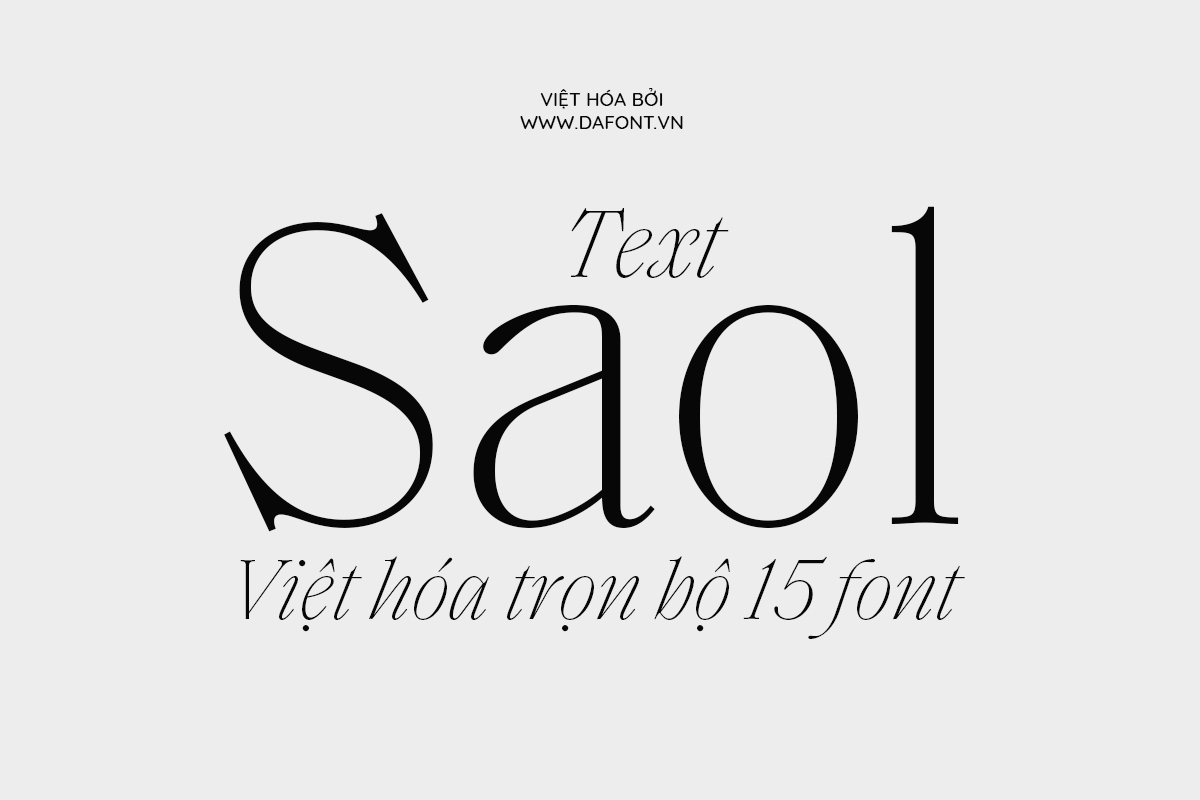
DFVN Saol Text Việt hóa (15 font)
DFVN Saol Text là một phần của bộ font Saol. Đây là phiên bản dành cho văn bản với các nét tương phản giảm để tránh các đường nét mảnh bị mất khi sử dụng ở kích thước nhỏ.
Saol Text bao gồm 7 kiểu đứng và 7 kiểu nghiêng cùng với 1 kiểu Monospaced (là phông chữ có độ rộng cố định, có các chữ cái và ký tự chiếm cùng một lượng không gian theo chiều ngang.)
DFVN Saol Text Việt hóa trọn bộ 15 font
Đặc điểm nổi bật của Saol Text
Phiên bản Text được tối ưu cho các kích thước nhỏ và có độ tương phản vừa phải, giúp tạo ra các hệ thống phân cấp kiểu chữ chi tiết, từ tiêu đề nổi bật đến văn bản dài dễ đọc. Saol Text thường được sử dụng trong các tạp chí và ấn phẩm, mang lại vẻ trang trọng và tinh tế.
DFVN Saol Text Việt hóa - 7 kiểu đứng
Saol Text với 7 kiểu đứng
• Độ tương phản vừa phải: Saol Text có độ tương phản vừa phải, giúp văn bản dễ đọc và không gây mỏi mắt khi đọc lâu.
• Nhiều trọng lượng: Font chữ này có sẵn 7 kiểu khác nhau từ Thin đến Bold, kèm theo phiên bản nghiêng tương ứng.
• Tối ưu hóa cho kích thước nhỏ: Bộ font được thiết kế để sử dụng ở các kích thước nhỏ mà vẫn giữ được độ rõ nét và dễ đọc.
Ứng dụng trong thiết kế
DFVN Saol Text Việt hóa - 7 kiểu nghiêng tương ứng
và 7 kiểu nghiêng tương ứng
• Tạp chí và ấn phẩm: Bộ font này thường được sử dụng trong các tạp chí và ấn phẩm để tạo ra các tiêu đề nổi bật và văn bản dễ đọc. Độ tương phản vừa phải giúp tạo ra sự cân bằng giữa tính thẩm mỹ và tính thực dụng.
• Thiết kế web: Trong thiết kế web, Saol Text có thể được sử dụng để tạo ra các nội dung đẹp mắt. Các trọng lượng khác nhau giúp tạo ra hệ thống phân cấp rõ ràng cho các tiêu đề, đoạn văn bản và chú thích.
• Thương hiệu: Saol Text mang lại vẻ sang trọng và tinh tế, rất phù hợp cho các thiết kế logo, bao bì sản phẩm và các tài liệu quảng cáo.
• Thiết kế đồ họa: Bộ font này có thể được sử dụng trong các thiết kế đồ họa như poster, banner và các tài liệu quảng cáo khác để tạo ra các tiêu đề nổi bật và văn bản dễ đọc.
• Thiết kế sách: Font chữ này cũng rất phù hợp cho việc thiết kế sách, từ bìa sách đến nội dung bên trong. Độ tương phản vừa phải giúp văn bản dễ đọc và không gây mỏi mắt khi đọc lâu.
DFVN Saol Text Việt hóa - Bộ font rất đẹp mắt
Saol Text phù hợp cho nhiều dự án thiết kế.
Dễ dàng kết hợp với nhiều kiểu font
Bạn có thể kết hợp với Saol Display để tạo ra một hệ thống phân cấp typographic hoàn chỉnh, từ tiêu đề nổi bật đến văn bản thân thiện với người đọc. Ngoài ra, bạn cũng có thể kết hợp tốt với các font chữ sans-serif để tạo ra sự cân bằng giữa cổ điển và hiện đại.
DFVN Saol Text Việt hóa - Dễ dàng kết hợp với nhiều kiểu font
DFVN Saol Text Việt hóa – Dễ dàng kết hợp với nhiều kiểu font tạo ra kiểu chữ đẹp mắt.
Bộ font DFVN Saol Text được việt hóa rất kỹ, từng dấu được tối ưu hóa lại. Ngoài ra, bộ font cũng được tối ưu hóa để bạn có thể dễ dàng sử dụng nó trong bất kỳ phần mềm thiết kế nào.